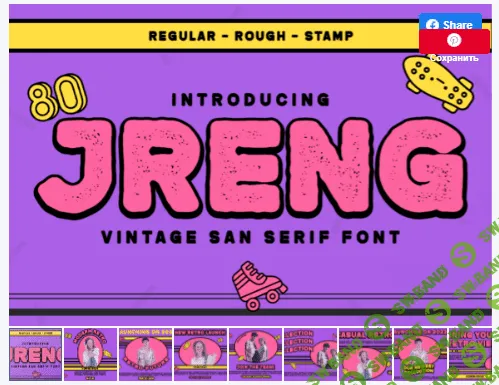
Название: Jreng Font (2021)
Jreng - это дисплейный шрифт с грубой текстурой и толстыми буквами. Этот шрифт идеально подходит для написания веб-дизайнов, визиток и всего остального, что требует смелого подхода.